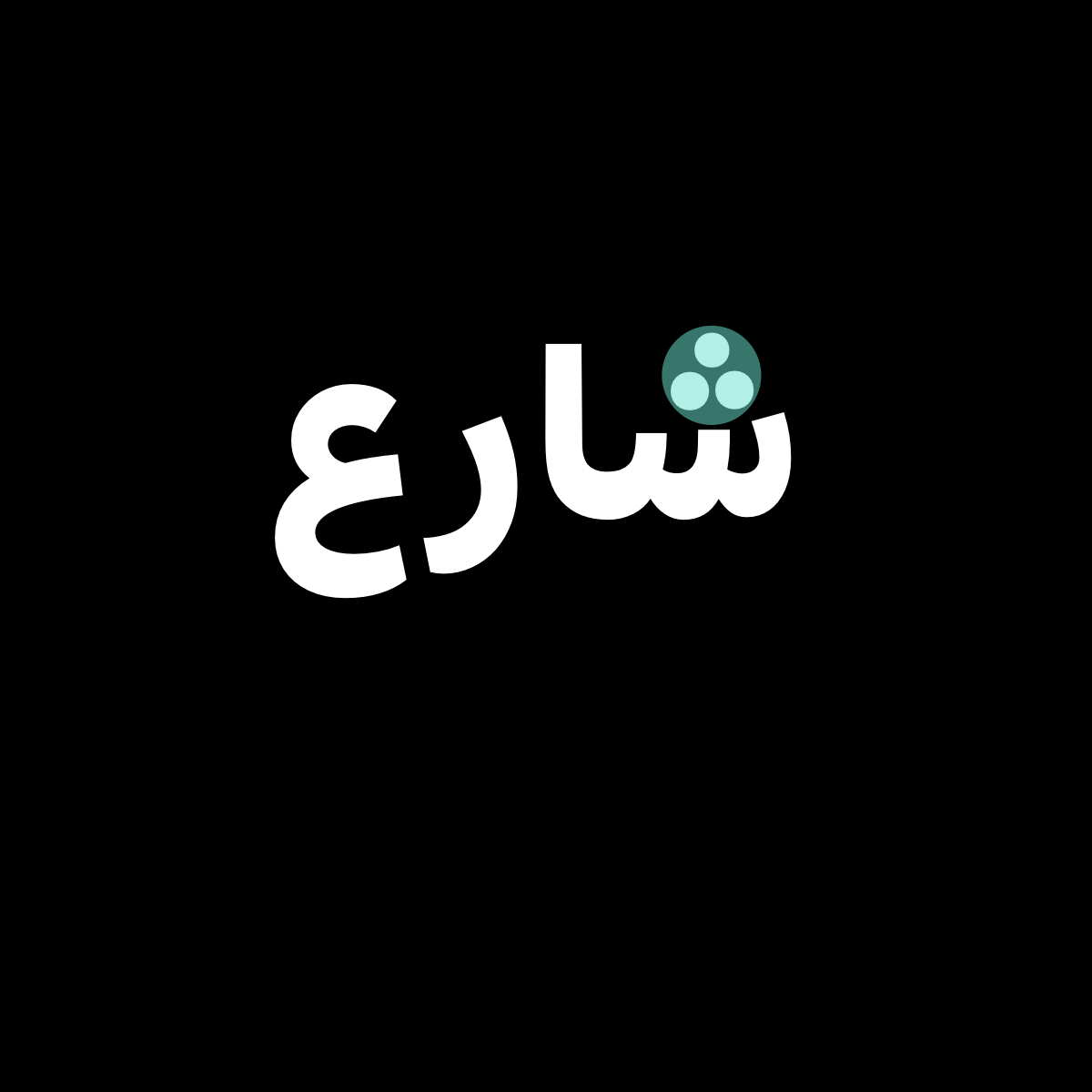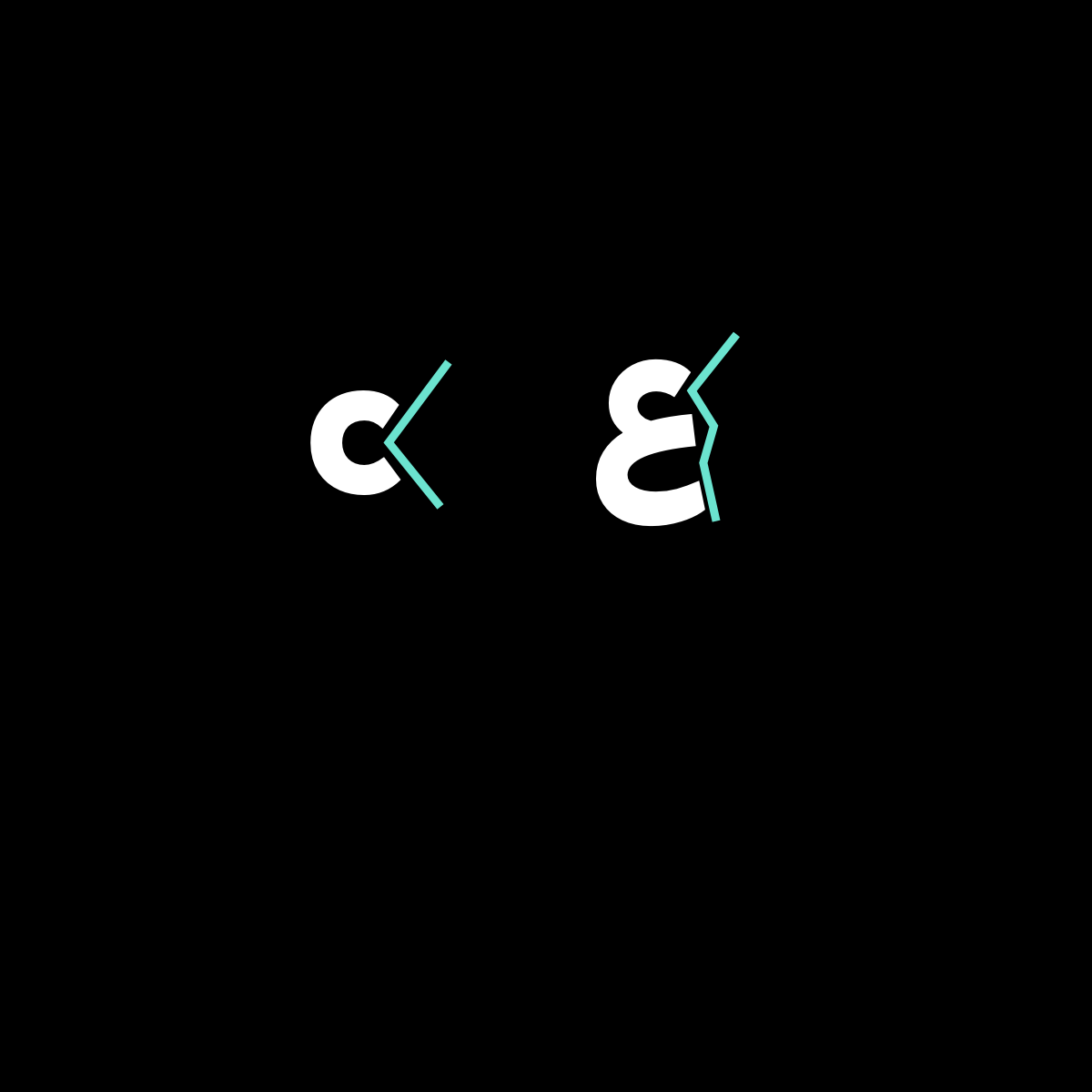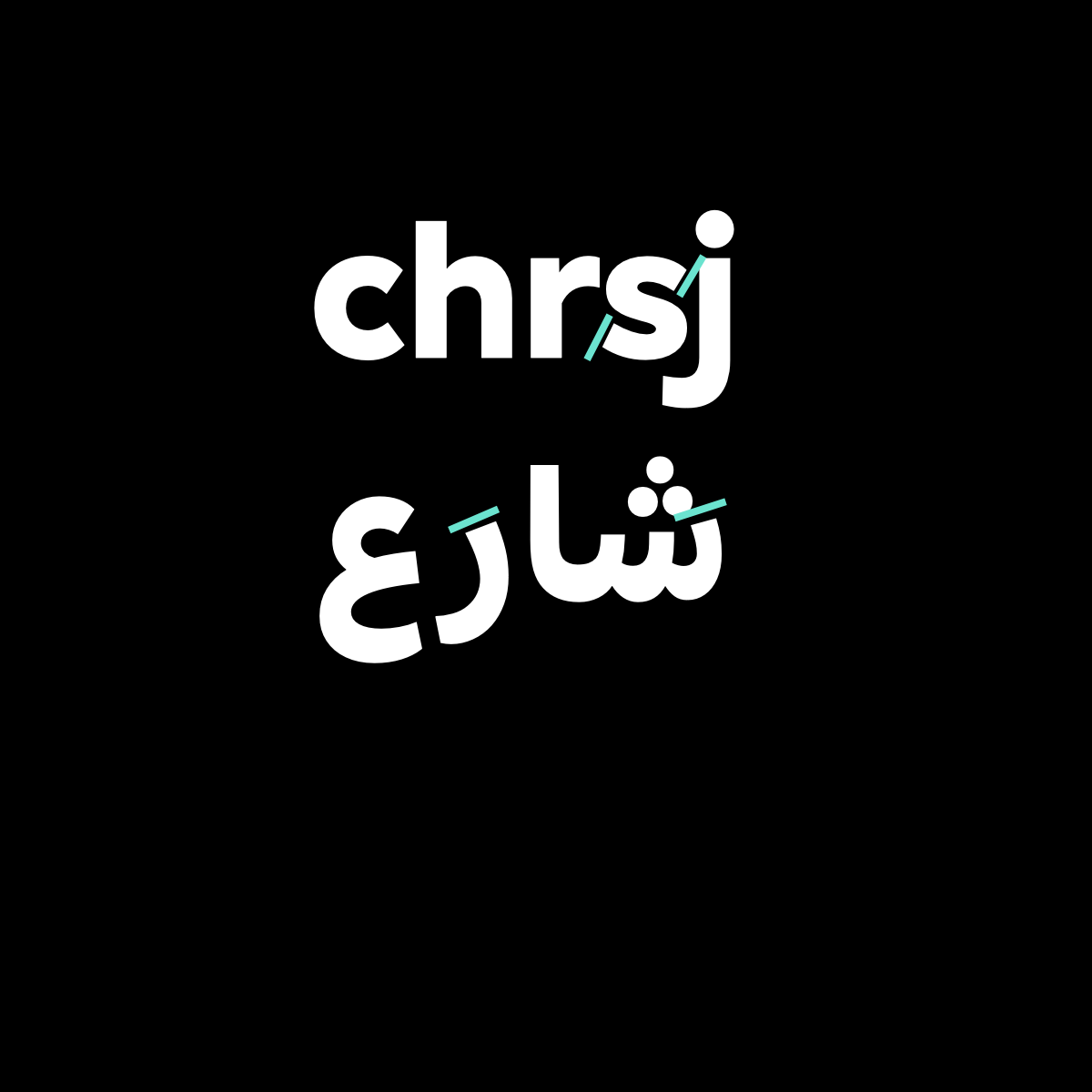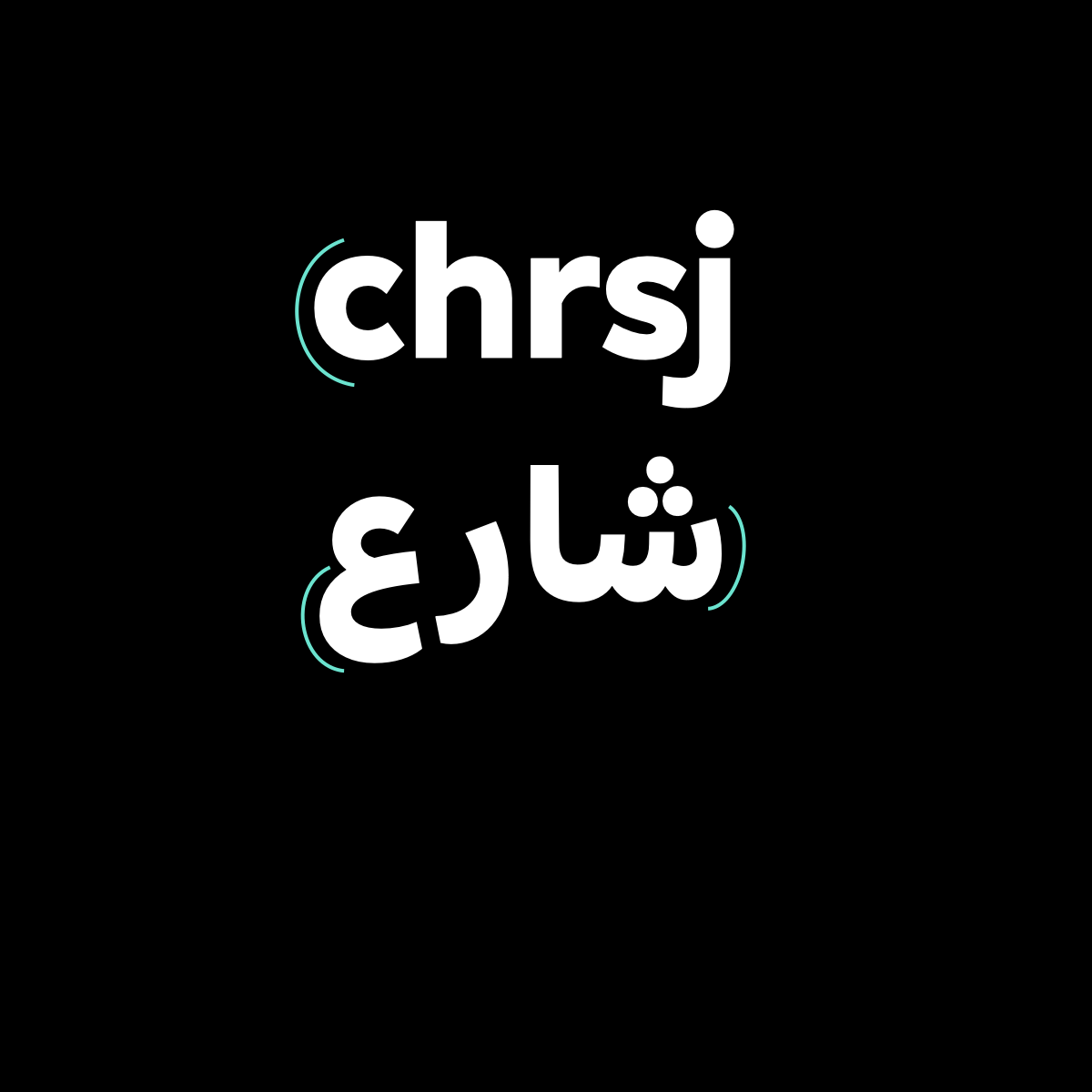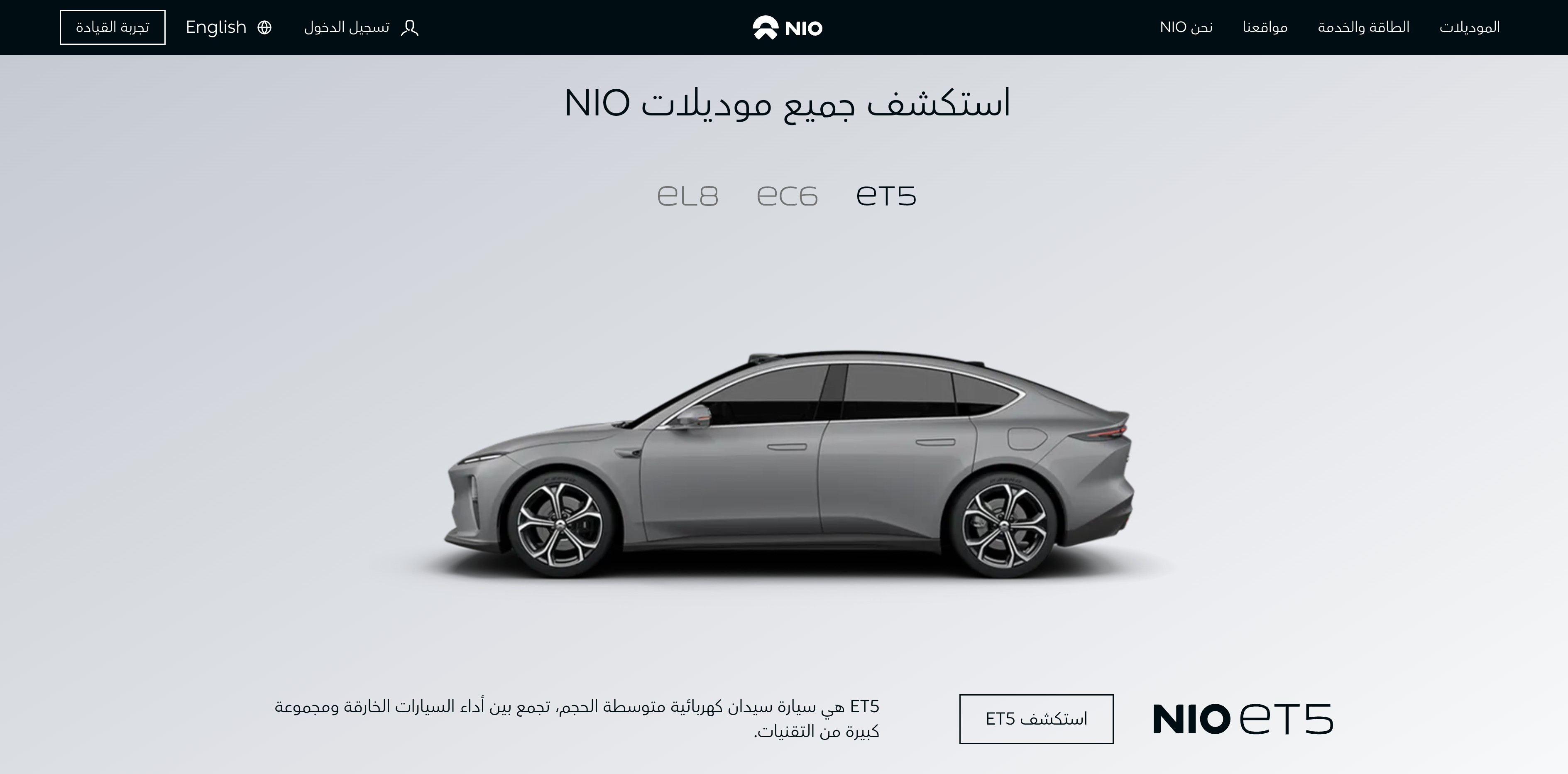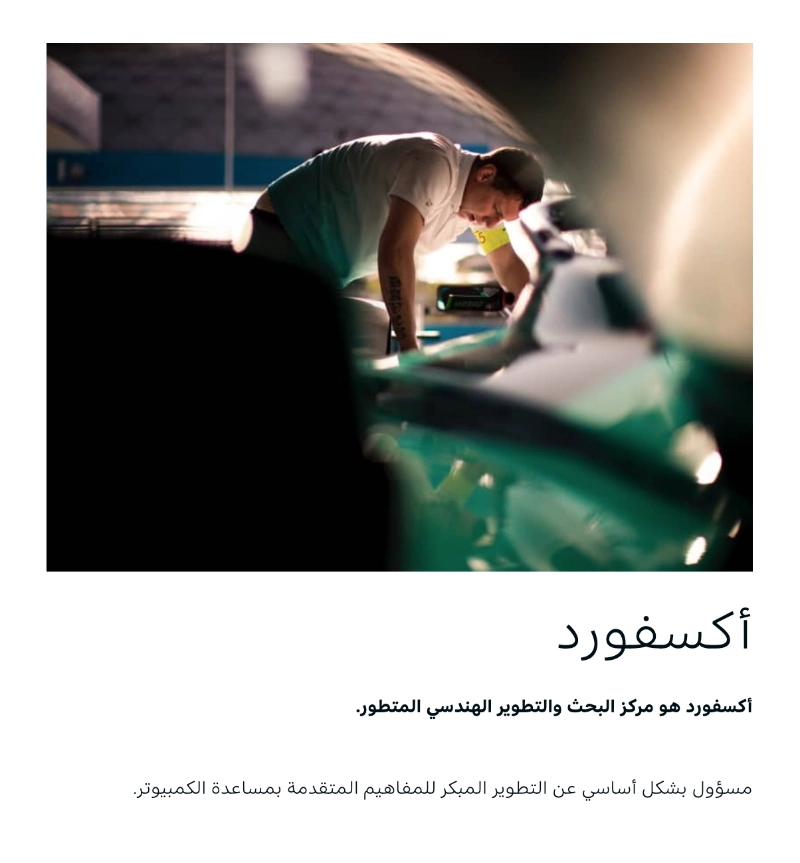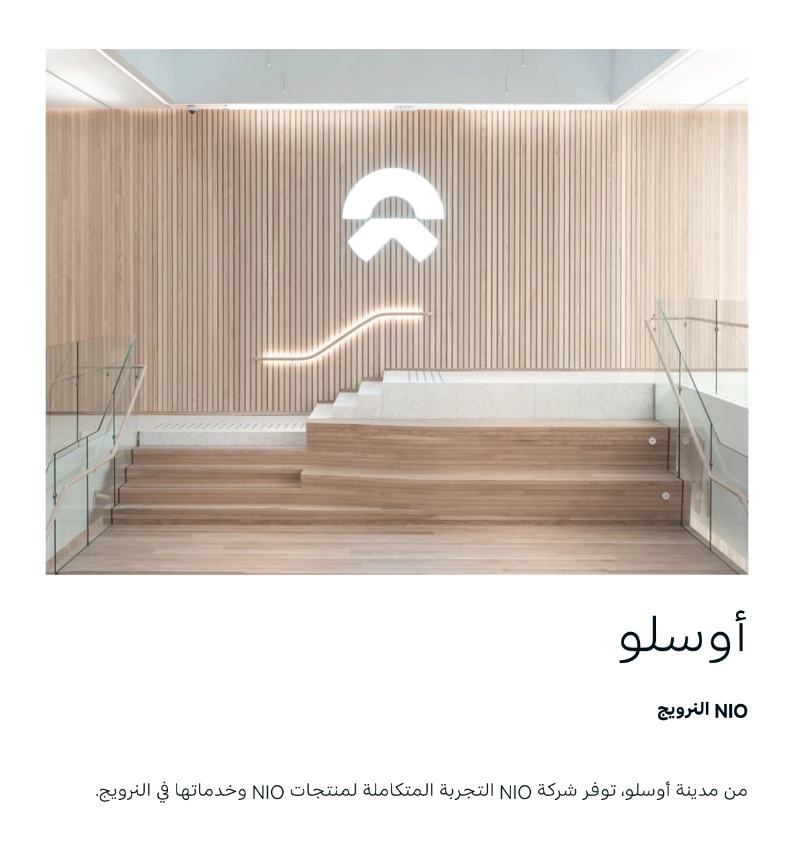
NIO × Monotype
خط عربي مخصص من NIO
NIO 蔚来汽车 · 阿拉伯语定制字体 Blue Sky Arabic
Project Background
项目背景
作为全球高端智能电动汽车的引领者,蔚来一直以创新科技和极致用户体验著称。自成立以来,蔚来不仅在中国市场树立了智能出行新标杆,更凭借前瞻的设计理念与用户共创体系,赢得了国际认可。其品牌精髓在于将先进技术与本地文化深度融合,使每一次出海都兼具视野与温度。
蔚来进军中东市场,是品牌国际化战略的重要一步。面对截然不同的文化环境与消费习惯,蔚来团队希望品牌可以真正建立信任,以全链路一致的体验引发共鸣,实现真正「本地共感」。
字重渐变 · 从轻盈到浑厚
HYBRID SOLUTION
融合解决方案:适配多场景下的阿拉伯语文字
阿拉伯语文字有独特的右起书写习惯和连写结构,对屏幕字体的可用性和美感有更加复杂的要求。从车机界面到官网排版、再到线下门店导视,每一个触点都是品牌本地化能力的体现。由此,蔚来联合蒙纳字库,共同打造既承载蔚来基因、又符合阿语美学的定制字体,专为中东市场开发 Blue Sky Arabic 字体,成为打通本地视觉壁垒的关键一步。
Blue Sky Arabic 充分尊重阿拉伯书写规范,并融合蔚来极简科技的风格基因,首先用于仪表盘和中控屏,确保信息传达高效且舒适。同时,品牌传播和广告搭配使用 Avenir Next Arabic,进一步强化视觉形象的高端统一。
蔚来重视线上线下的无缝体验统一。无论是阿布扎比的 NIO House,还是迪拜 NIO Space,均从建筑设计到视觉导视,深度融合阿拉伯字体与高科技美学理念。定制字体贯穿门店导示、互动屏、墙体装饰等每个细节,确保用户在多场景里都能获得连贯且沉浸的体验。
Blue Sky Arabic Variable可变字体版本
MULTILINGUAL CONSISTENCY
多语协同的设计细节
蒙纳团队基于 Blue Sky 西文字体的特征,精心调校每一个阿拉伯字母细节,确保两者视觉融合统一。西文与阿文均采用开阔字腔、斜切笔尾及圆润饱满的字形;同时通过加大阿文圆点,有效提升了小字号的显示效果与可读性。
تفاعل النص مع الضوء والظل
Light and Shadow
شاهد كيف يحافظ خط Blue Sky Arabic على وضوحه وتوازنه البصري عند التبديل بين الأنماط اللونية المختلفة.
تتطلب القراءة في الـ Dark Mode موازين بصرية دقيقة. تم تحسين حروف "بلو سكاي" لتقليل توهج الحروف البيضاء على الخلفية السوداء، مما يجعل تجربة القراءة الطويلة Reading Experience أكثر راحة للعين.
أما في الوضع الفاتح Light Mode، تبرز جماليات رسم الحرف والوصلات الدقيقة، مما يعكس نقاء التصميم والاهتمام بالتفاصيل التي تجعل من الـ Typography عنصراً أساسياً في نجاح أي تصميم.
يدعم الخط دمج اللغة الإنجليزية Bilingual Support بشكل طبيعي، حيث تتوافق الحروف اللاتينية تماماً مع موازين الحروف العربية، مما يخلق وحدة بصرية Visual Unity شاملة للمحتوى العالمي.
سواء اخترت الخلفية السوداء أو الرمادية الفاتحة، فإن الخط يظل ثابتاً في حضوره القوي. نمنح المصمم أداة قوية للتحكم في الـ Editorial Hierarchy لبناء هويات بصرية Visual Branding متميزة.
Building Trust
细节锻造信任,打造品牌长久口碑
蔚来中东本地化体验案例,真实展现了全球高端品牌如何用「细致入微」的视角构建市场信任。每一次视觉升级、每一轮体验叠代,既回应了本地文化,也赋予了品牌成长新的价值内涵。蔚来以科技融汇生活,以细节致敬用户,在多元市场持续夯实长久口碑与商业竞争力。